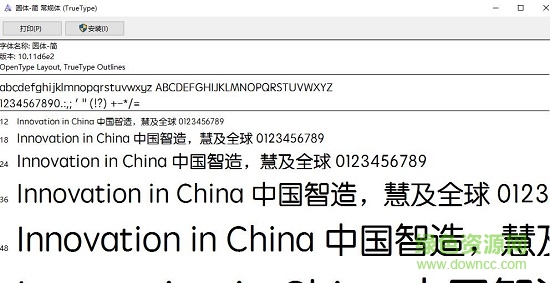
圓體簡(jiǎn)免費(fèi)字體
圓體-簡(jiǎn) 常規(guī)體是一款粗細(xì)適中的圓體字體,該字體的拐角處均是圓形,給人的感覺(jué)比較溫柔,沒(méi)那么犀利,需要更多ttf字體的小伙伴們快來(lái)綠色資源網(wǎng)下載吧!
圓體簡(jiǎn)字體
圓體的變體有哪些?
變體有為幼圓體、琥珀體等,字體清晰、端正、嚴(yán)肅,適合于報(bào)紙大字頭、圖書(shū)封面、招牌、廣告、網(wǎng)站標(biāo)題的制作。